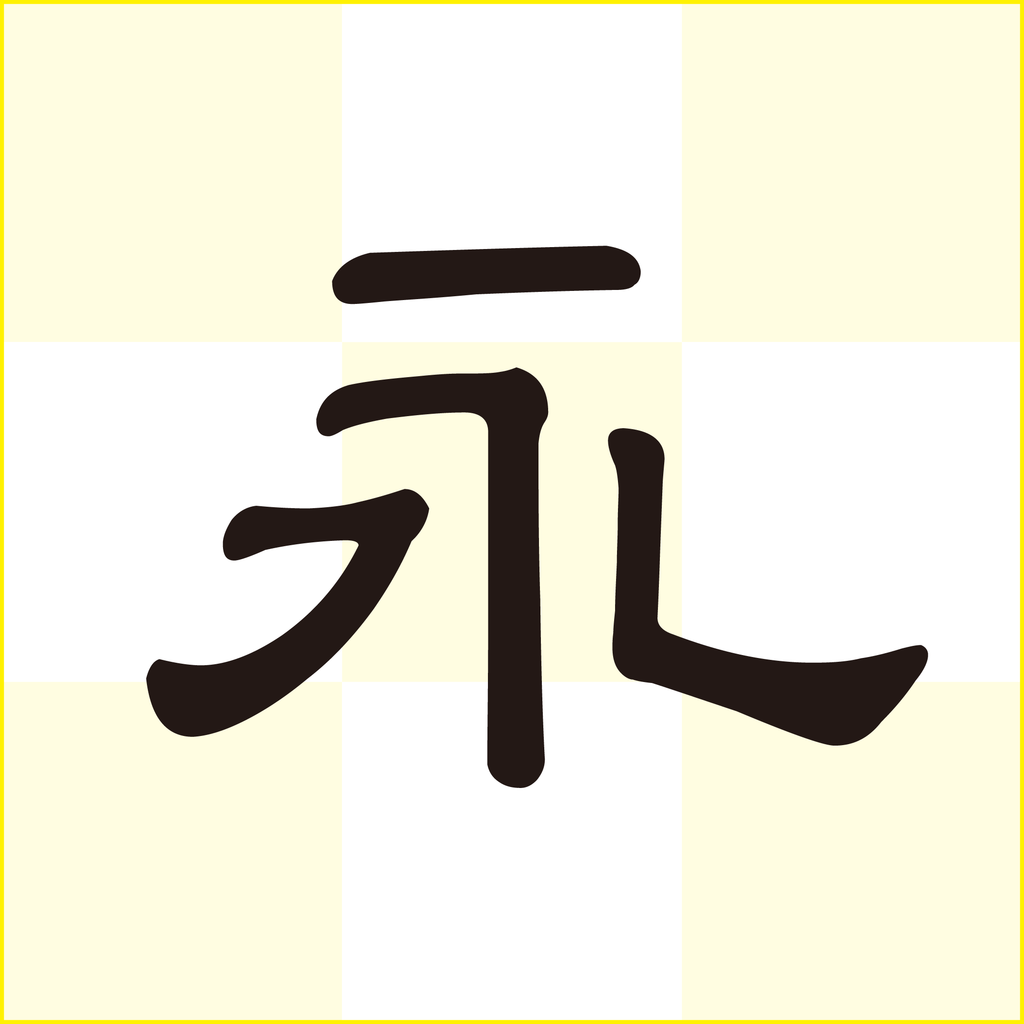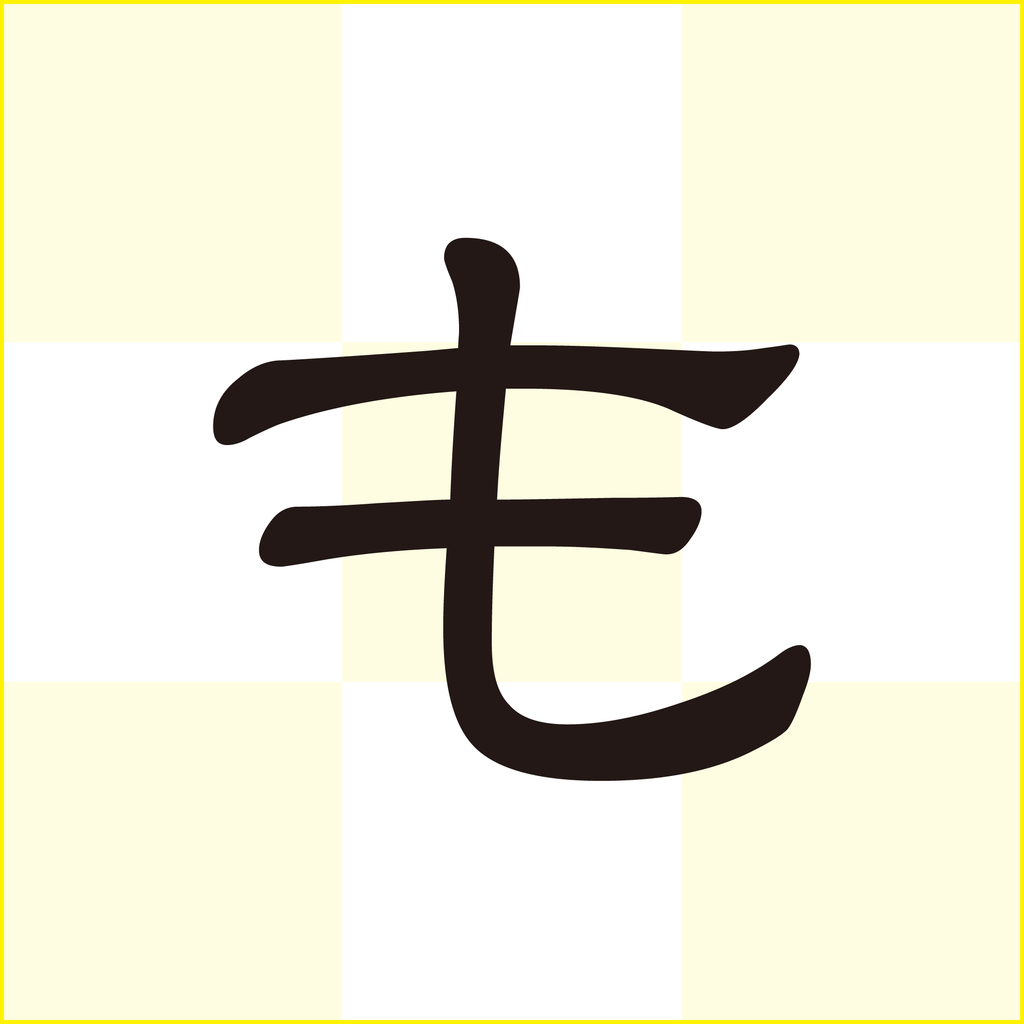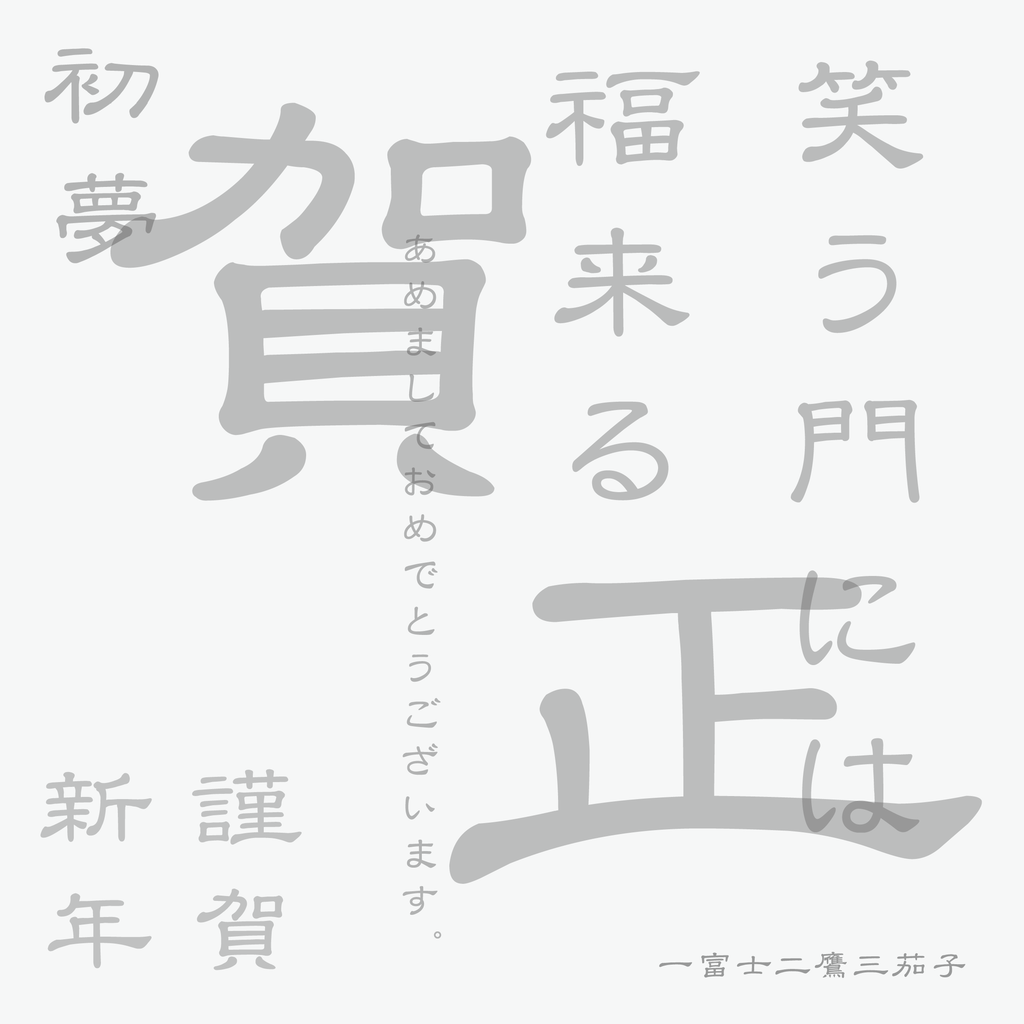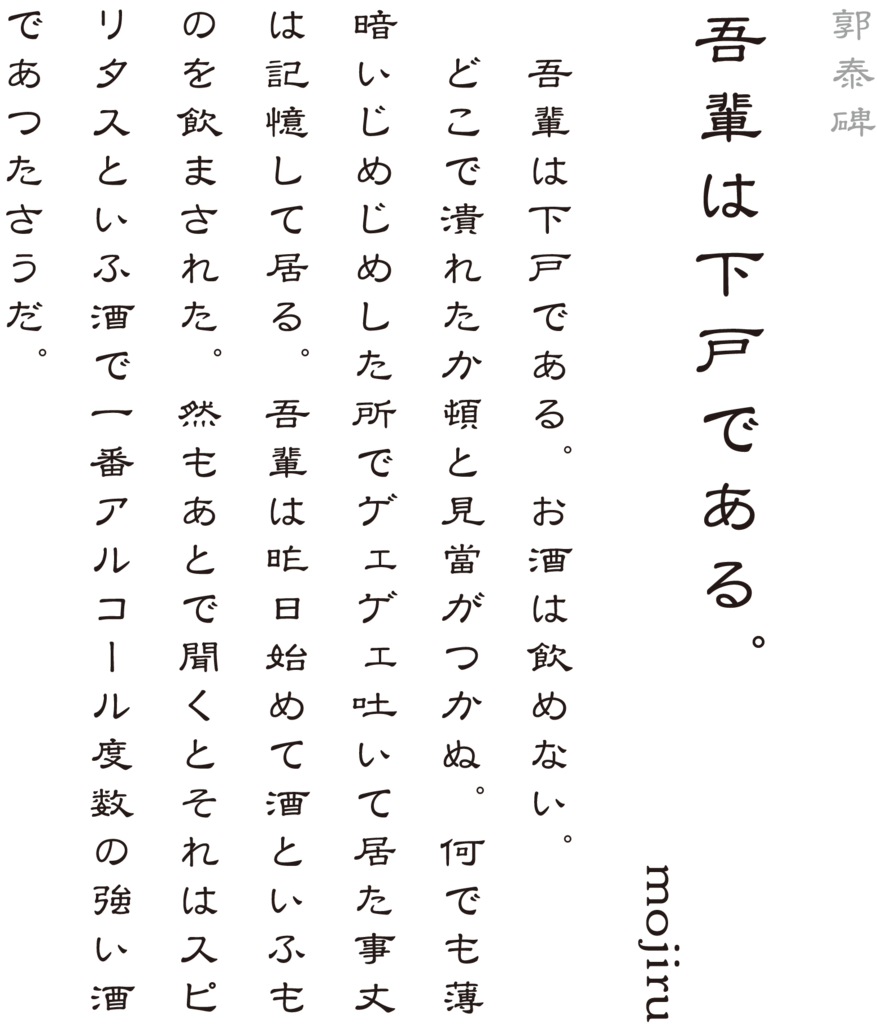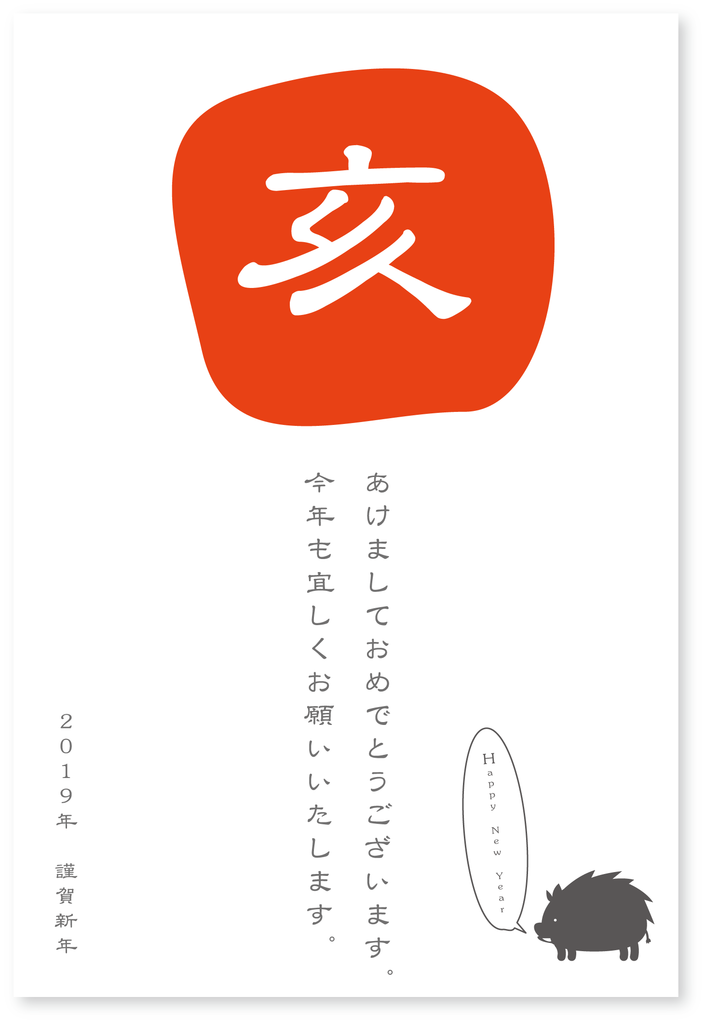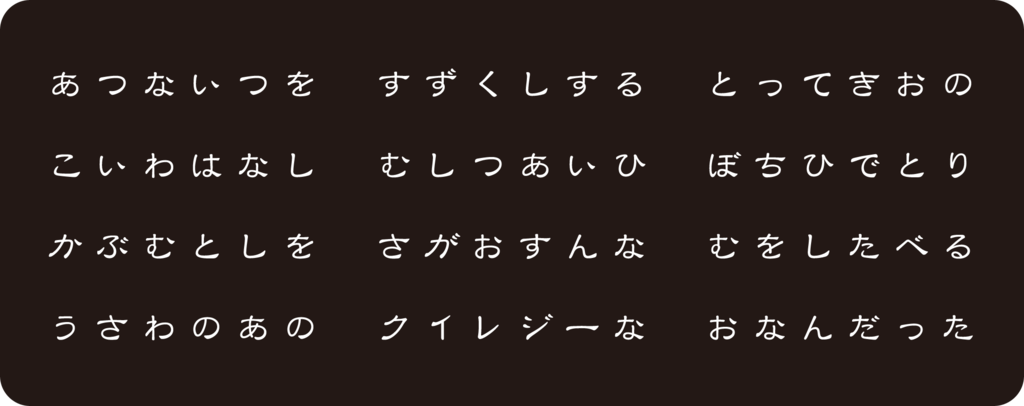
郭泰碑
郭泰碑に使用されていた文字をベースに、変化に富んだ筆画の美しさで伝統的な隷書の風格を表現している書体。波磔((はたく)という波を打つような左右のはらいと、向勢(こうせい)と背勢(はいせい)の境目がはっきりしており、ふところが狭めで起筆は蔵峰、終筆は波磔の波打つような動きのある美しさが特徴になっている。タイトルなどに使用することで、優美で古風な文字のイメージを作り出すことができ、雑誌やポスター、製品パッケージなどにも適している。
郭泰
中国後漢代の儒者。当時の名儒を数え上げた八顧の一人。
郭泰碑 文字見本